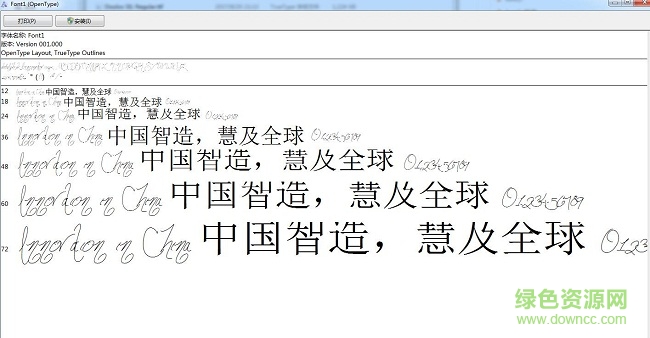
font1-普通字體
font1-普通字體是一款非常漂亮的花體字體,這款字體顏色淺、線條細,行筆婀娜,結(jié)體婉轉(zhuǎn),富有韻律,具有動勢美感,另外還附帶有font142字體,需要的朋友快來下載吧!
花體字體介紹
花體需要柔軟的有彈性的筆尖去表現(xiàn)粗細的變化、用較細的筆尖尖端去表現(xiàn)游絲的生動!多見于電影書信和封面裝飾!
font1-普通字體
font1字體特點
字體優(yōu)美清新,線條流暢,給人以華麗柔美之感,此種類型的字體,適用于女用化妝品、飾品、日常生活用品!